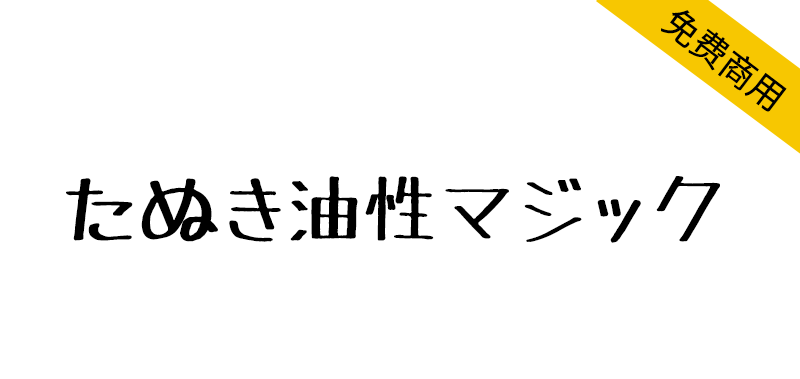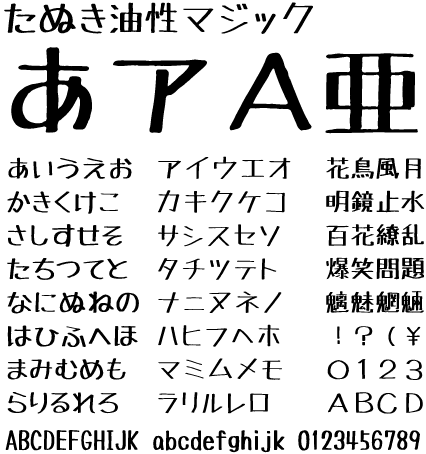
TanukiMagic(日文名:たぬき油性マジック)是用油性极粗线条在普通纸上写的手写文字制作的免费日语字体。收录了平假名、片假名、英文数字、符号、JIS第二水准的汉字以及移位IBM扩展汉字。想用贺年卡和流行音乐等表现手写风格的时候推荐使用,商务使用也可以免费自由使用。
普通紙に油性極太マジックで書いた手書き文字から作成した無料日本語フォントです。ひらがな・カタカナ・英数字・記号、JIS第二水準までの漢字及びシフトIBM拡張漢字を収録しています。年賀状やポップなどで手書きっぽさを出したいときにお勧めです。 商用での利用も、無料でご自由にお使いいただけます。